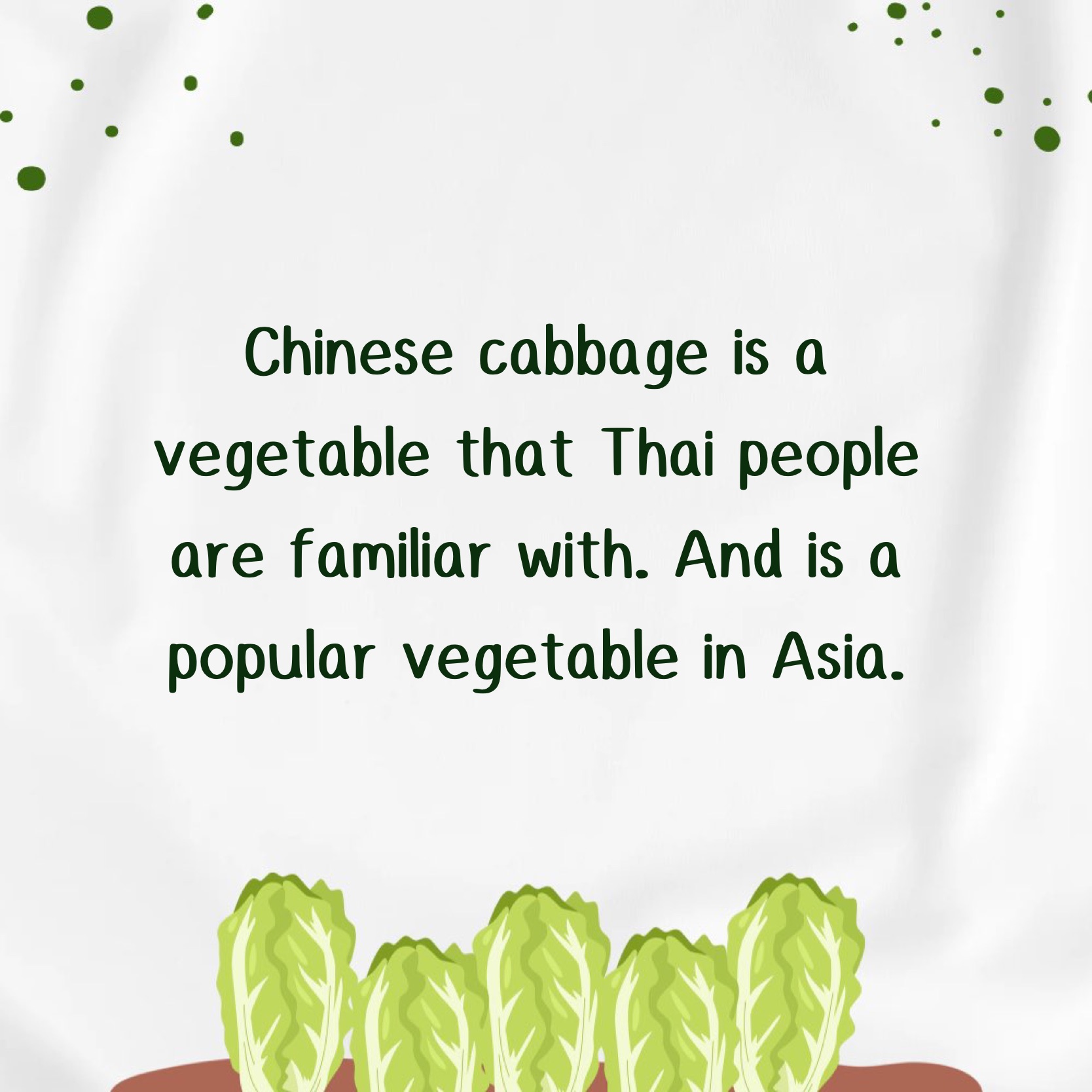
ผักกาด (Pakkad)
แจกฟรี!! ฟอนต์ลายมือ ผักกาด (Pakkad)
เป็นฟอนต์ลายมือหัวทึบ สามารถใช้งานได้หลายรูปแบบไม่ว่าจะเป็น การจดโน็ต สรุปงาน ตกแต่งป้ายสินค้า โปสเตอร์ หรือใช้ตกแต่งรูปภาพ/วิดีโอและโฆษณาสินค้าต่างๆก็ได้เช่นกัน